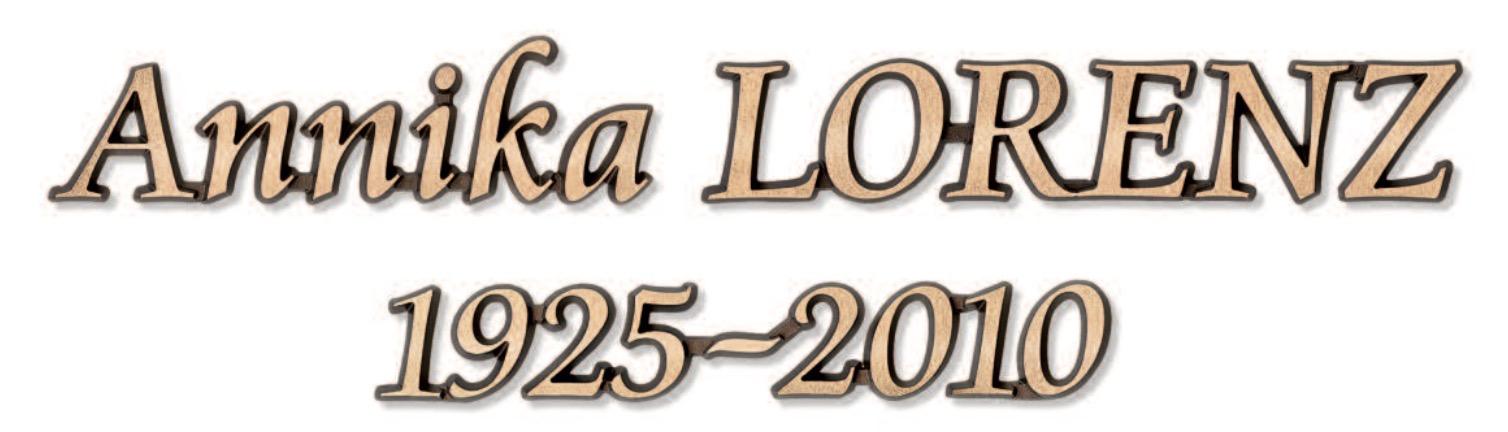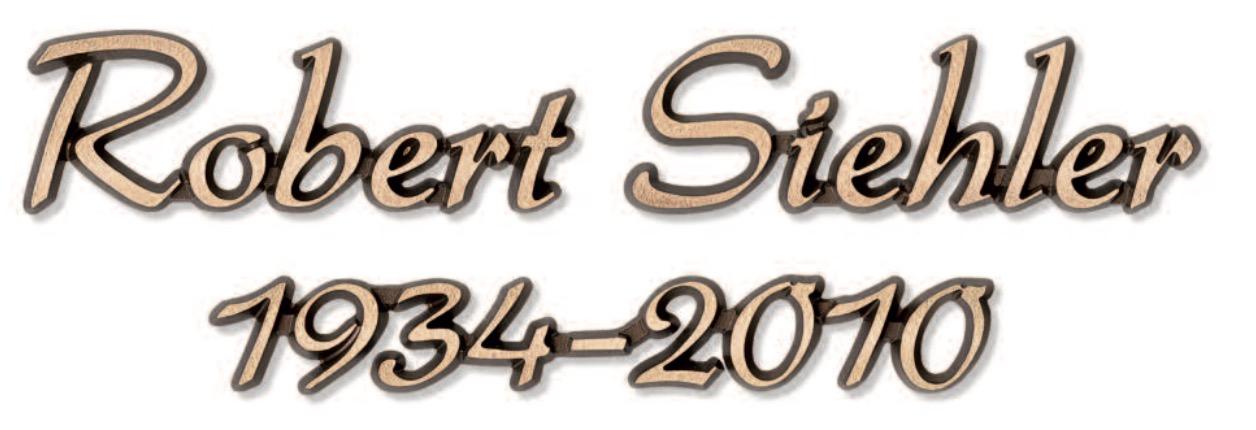
Suche Bronzeschriften entsprechenden Font
Seit einigen Jahren bietet die Kunstgiesserei Strassacker aus Metallplatten herausgefräste Schriften an. Die meisten Schriften basieren auf einer gewöhnlichen Satzschrift, welche nur leicht modifiziert ist. Da die Ergebnisse der Gestaltungssoftware jener Giesserei sehr zu wünschen übrig lassen, erstelle ich die Schriftentwürfe mit dem Affinity Designer. Mehrere Versuche, von der Firma den passenden Font zu erfahren, sind nicht geglückt. Vielleicht kennt die jemand von euch?